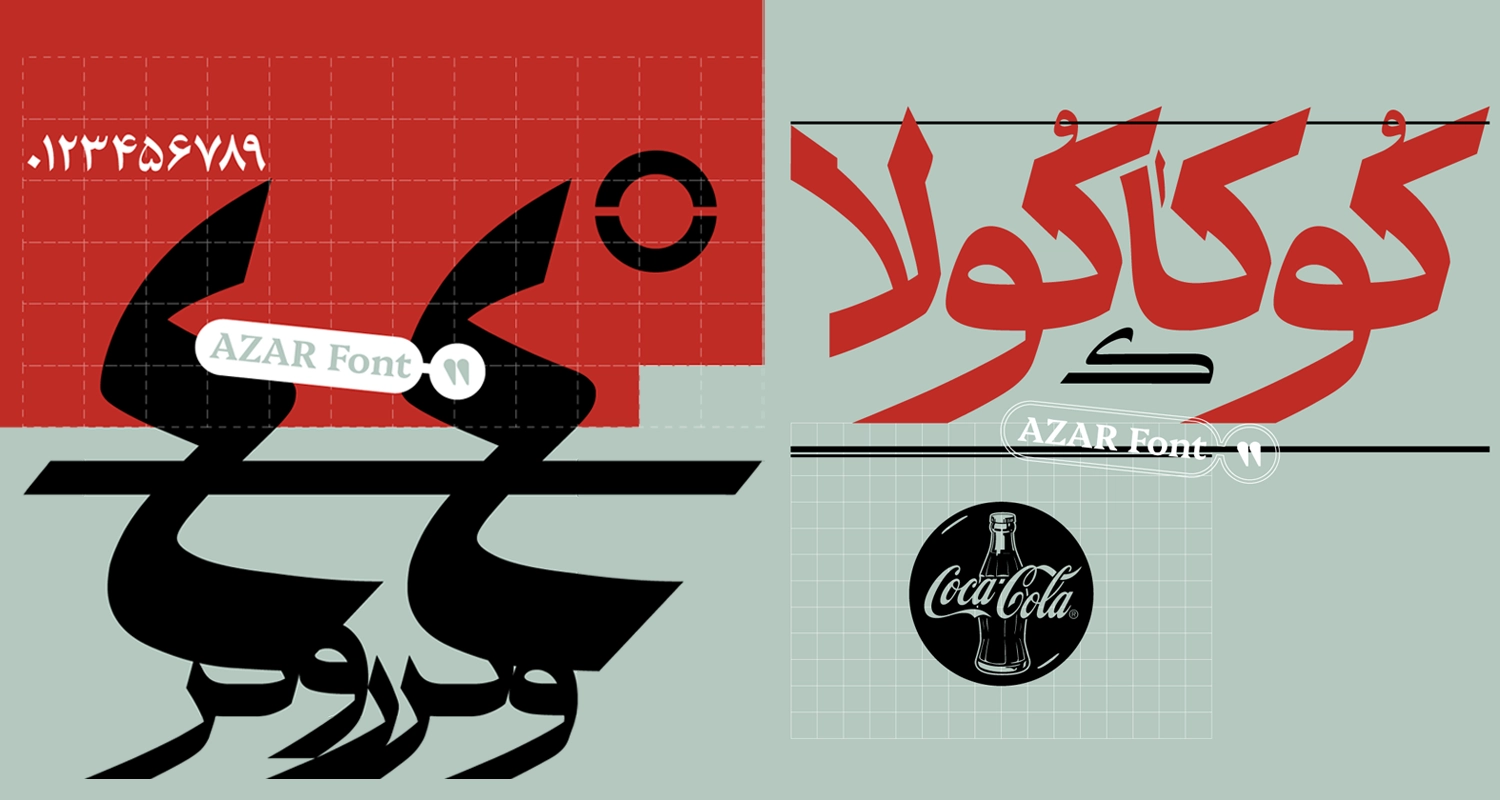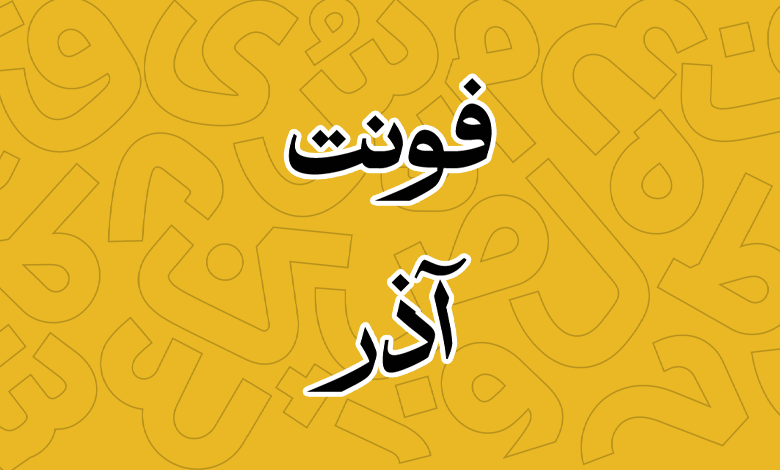
فونت آذر (Azar)
فونت آذر (به انگلیسی: Azar) تلفیقی هوشمندانه از الهامات کلاسیک (خط ثلث) و تناسبات مدرن است که با هدف تبدیل به یک فونت نرم‌افزاری برای استفاده در طراحی‌های امروزی ساخته شده است. از این فونت که دارای یک وزن معمولی است می‌توانید در عناوین، به‌خصوص طراحی پوستر استفاده کنید. فونت آذر رایگان نیست و در قالب یک بسته با یک وزن معمولی ارائه شده است.
این فونت فارسی با طراحی منحصربه‌فردش، انتخابی ایده‌آل برای عناوین و تیترهای کتاب‌ها، روزنامه‌ها، وب‌سایت‌ها و انواع پروژه‌های گرافیکی تبلیغاتی محسوب می‌شود. خوانایی بالا و ظاهر امروزی آن به طراحان کمک می‌کند تا در عین حفظ اصالت و ریشه‌های سنتی، طرح‌هایی مدرن و چشم‌نواز خلق کنند.
در ادامه به نقد و بررسی فونت Azar خواهیم پرداخت؛ قلمی که از خط نسخ بهره می‌برد و با ارث‌بری از مقداری خط ثلث، ظاهری مدرن و امروزی به نوشته‌های شما خواهد داد. خصوصا در متون کوتاه و عناوین که نیاز دارید جنبه نمایشی داشته باشند.
فونت آذر در محیط‌های چاپی مانند نشریات و کتاب‌ها، می‌تواند ظاهری جذاب و شکیل به متون ببخشد؛ و در عین‌حال برای فضاهای دیجیتال مانند وب‌سایت‌ها و بنرهای تبلیغاتی، انسجام و خوانایی خود را به خوبی حفظ می‌کند.
استفاده از فونت آذر در فضاهای تجاری و فرهنگی، به دلیل ساختار متناسب و طراحی روان، می‌تواند به‌خوبی پیام را به خواننده انتقال داده و قدرت جذب بالایی هم داشته باشد. این فونت برای برندهایی که به دنبال هویت بصری کلاسیک اما مدرن هستند، گزینه‌ای بسیار مناسب به شمار می‌آید. ظرافت در فرم حروف و تعادل در ساختار کاراکترها، سبب می‌شود که فونت آذر بدون ایجاد شلوغی بصری، به زیبایی در مرکز توجه قرار گیرد.
1. فونت آذر؛ حفظ اصالت در عین مدرنیته
فونت آذر دارای ریشه‌های کهن خط ثلث در ساختار خود است، اما با اصلاح تناسبات و طراحی مینیمال، ظاهری نوین و کاربردی یافته است. این فونت با تلفیقی بین سنت و مدرنیته، از طرفی پاسدار اصالت خطوط سنتی مانند ثلث است و از سوی دیگر با رعایت سادگی و پیراستگی، ظاهری مدرن دارد. چنین ترکیبی به طراحان این امکان را می‌دهد که از فونت در عناوین و تیترها بهره ببرند، بدون اینکه طرح قدیمی یا کلیشه‌ای به نظر برسد.
یکی از نقاط قوت فونت آذر، بازنگری کامل کاراکترها و ویرایش نرم‌افزاری دقیق حروف است. کلیه حروف و جزئیات بازنگری شده‌اند تا با استانداردهای ساخت فونت امروزی هم‌آهنگ شوند. این اصلاحات باعث شده کاراکترها بدون ایجاد شلوغی یا پیچیدگی اضافی، خوانایی بهتری داشته باشند. ولی با این‌حال شخصیت اصلی تایپ‌فیس به خوبی حفظ شده است.
1. طراحی خاص گلیف‌ها
تک‌تک کاراکترها و گلیف‌های این فونت با ظرافت طراحی شده‌اند. فرم‌هایی روان که دارای ساختار هندسی منسجمی هستند. این ویژگی در حروفی مانند «ر، ک، ل» به خوبی مشهود است. طراحی چشمی‌ها هماهنگ و یک‌دست است و تعادل بصری بالایی ایجاد کرده که برای عناوین و متون کوتاه ایده‌آل است.
با وجود الهام از خط ثلث، خوانایی حروف در فونت آذر بسیار خوب است. این ویژگی باعث می‌شود که فونت در اندازه‌های کوچک‌تر هم کارایی خود را حفظ کند. این فونت برای تیترها و عناوین کتاب‌ها، روزنامه‌ها و وب‌سایت‌ها بسیار مناسب است و می‌تواند ظاهری شکیل و مدرن به طرح‌ها ببخشد.
برای طراحی‌های تبلیغاتی، لوگوها و پوسترها، فونت آذر می‌تواند گزینه‌ای ایده‌آل باشد؛ چرا که ترکیب سادگی و اصالت را همزمان ارائه می‌دهد.
این فونت که از زبان‌های فارسی و عربی پشتیبانی می‌کند، امکان تایپ کلمات را با حروف جایگزین و برخی ترکیبات دوتایی نیز در اختیار قرار می‌دهد. برخی حروف جایگزین شامل «ـر، ترکیبات ک، ترکیبات گ» هستند. همچنین حروف «ر، و» مشابه با تصاویر بالا امکان تایپ در دو حالت حروف کوتاه و کشیده را دارند.
فونت آذر؛ انتخابی درخشان برای طرحی پوستر
فونت آذر با ترکیب هوشمندانه‌ای از ظرافت سنتی و ساختار مدرن، گزینه‌ای ایده‌آل برای طراحی پوسترهای جذاب و تاثیرگذار به شمار می‌آید. حروف نرم و روان این فونت با خطوط کرسی منظم و چشمی‌های متعادل به راحتی پیام شما را به مخاطب منتقل می‌کند.
در طراحی پوسترهایی که هدف آن جلب توجه فوری و برقراری ارتباط سریع است، فونت آذر با خوانایی بالا و ظاهر چشم‌نواز خود، نقش کلیدی ایفا می‌کند. ترکیب این فونت با المان‌های گرافیکی به شما اجازه می‌دهد پوسترهایی با هویت بصری منحصربه‌فرد خلق کنید که در ذهن مخاطب ماندگار شوند.
این فونت به دلیل ویژگی‌های ظریف و در عین حال قدرتمند خود، به راحتی می‌تواند در پوسترهای کتاب‌ها، رویدادهای هنری، همایش‌ها و کمپین‌های تبلیغاتی بدرخشد. فونت آذر، هماهنگی لازم را برای استفاده در عناوین بزرگ و جزییات ظریف پوستر فراهم کرده و به شما این امکان را می‌دهد که پیامی را با صدایی واضح و رسا به مخاطبان منتقل کنید.
فونت آذر که از دو زبان فارسی و عربی پشتیبانی کاملی دارد، در قالب یک وزن معمولی Regular اما با ضخامت سیاه ارائه شده است. در این فونت برخی ترکیبات جایگزین نیز وجود دارد که به نمایشی‌تر کردن کلمت و طراحی شما کمک می‌کند.
تغییرات نسخه ۱.۲ فونت آذر:
• برطرف شدن مشکلات مربوط به فاصله‌ی «و» با برخی لیگچرها.
• اصلاح تفاوت فرم «ر» در برخی لیگچرها.
• اصلاح ناهم‌آهنگی ضخامت در اتصال برخی از حروف.
• اصلاح اعوجاج فرمم‌های ‍«فـ» و ‍«ـف».
• اصلاح جاگذاری اعراب پایین «چ».